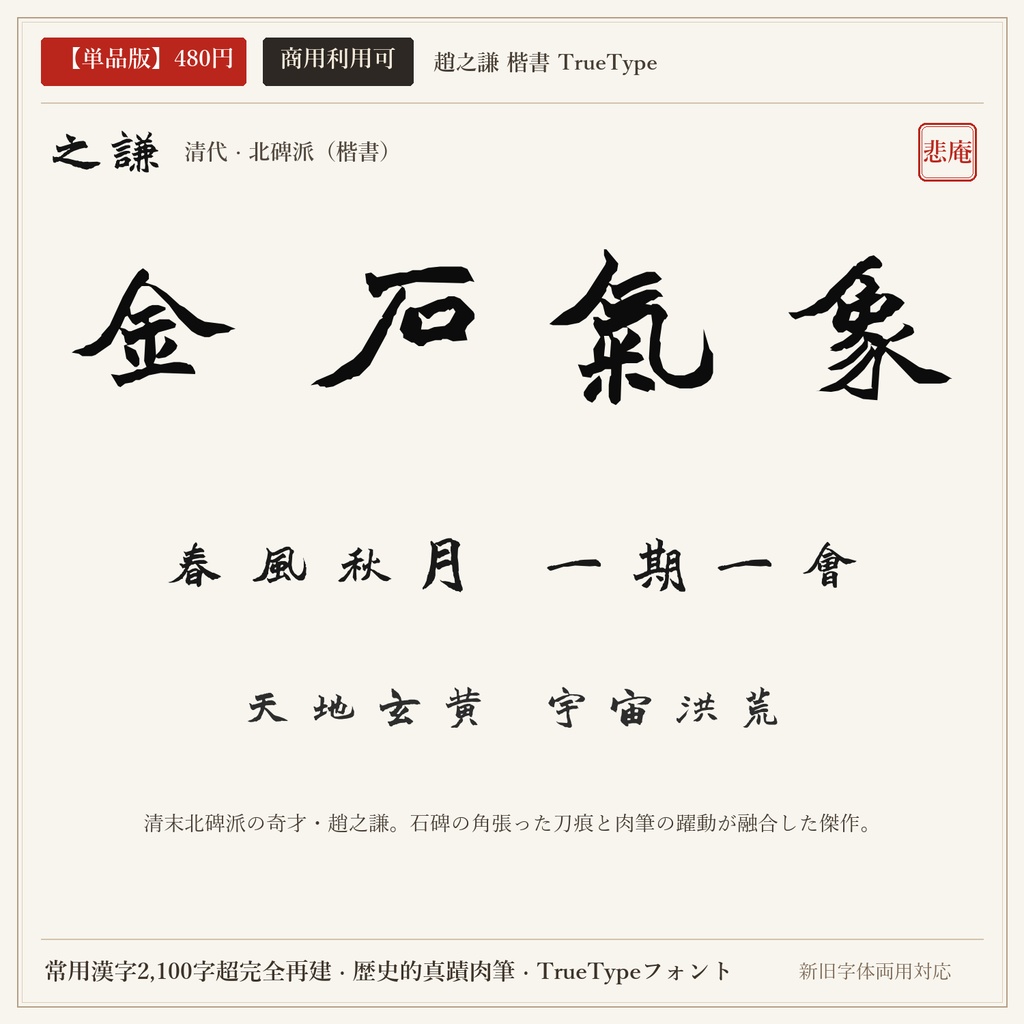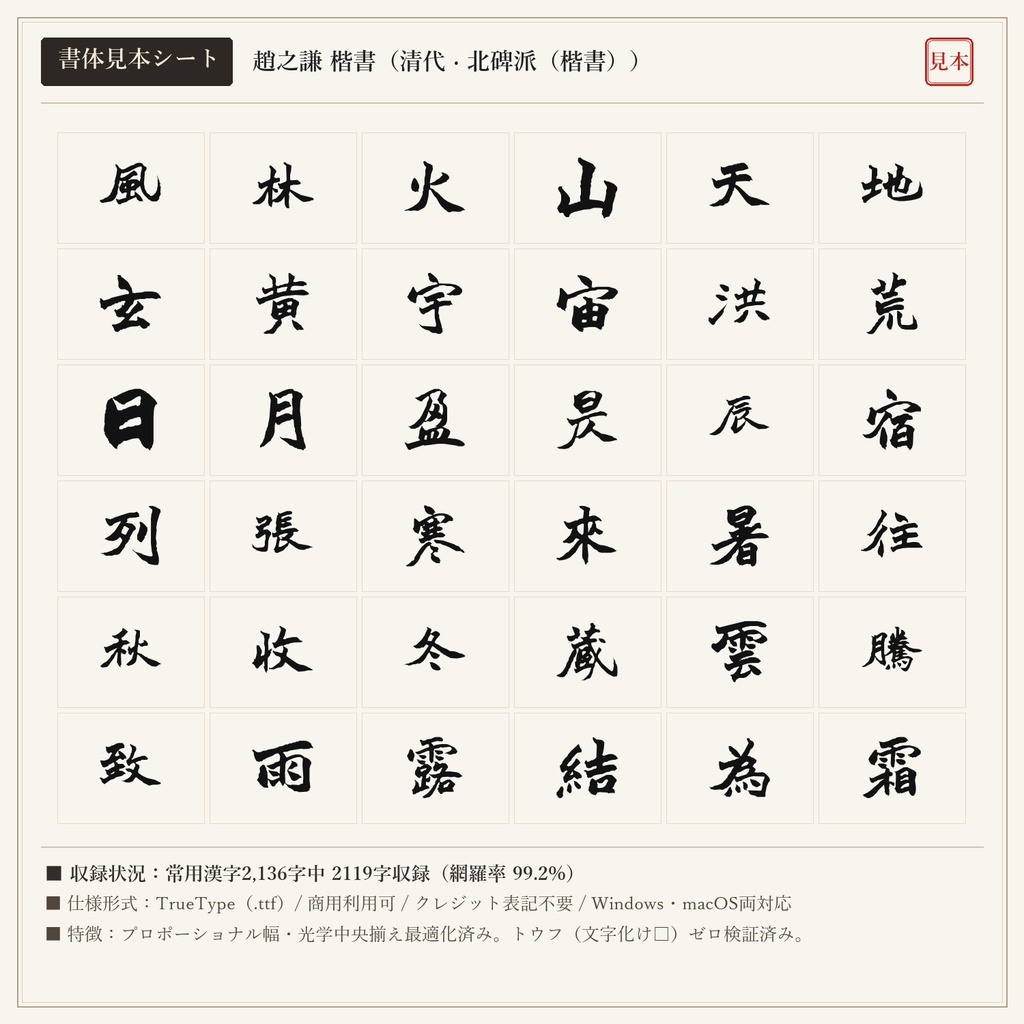
【単品版】趙之謙 楷書フォント|清代北碑派の巨匠・魏碑肉筆の雄渾・商用利用可
清末の書画・篆刻の巨星・趙之謙の北碑楷書から制作したフォントです。北朝石刻の角張った剛健さと、筆の弾力を生かした伸びやかな運筆が融合した、極めてモダンで力強い造形美を持ちます。 ■ 本フォントの特徴 ・常用漢字2,136字中、2119字を高精度収録(網羅率 99.2%)。 ・現代の新字体を入力しても、歴史的な真蹟字形・旧字体が自然に出力されるデュアルマッピング対応。 ・文字ごとの最適なプロポーショナル字幅設定により、自然で流麗な連綿と墨の息遣いを再現。 ・トウフ(文字化け□)を出さない事前フォントマッピング検証済み。 ■ 未収録文字一覧(全17字) 歴史的真蹟・拓本に存在しない以下の字種は未収録(非対応)となります。ご購入前にご確認ください。 丼 厘 峠 扱 拶 枠 栃 桁 濫 碁 線 脊 著 込 郷 闘 駄 ■ 形式 TrueTypeフォント(TTF) / Windows・macOS両対応 ■ 利用規約 個人・法人の商用利用OK。クレジット表記不要。 ロゴ、動画、ゲーム、書籍、同人誌、配信サムネイル、Web、印刷物、グッズ等に自由にご使用いただけます。 フォントファイル自体の再配布・共有・販売・転売は禁止です。 ※東晋の王羲之(行書)と盛唐の顔真卿(楷書)を同梱した「【無料版】王羲之 + 顔真卿 2書体セット(0円)」もショップ内にて無料配布中です。